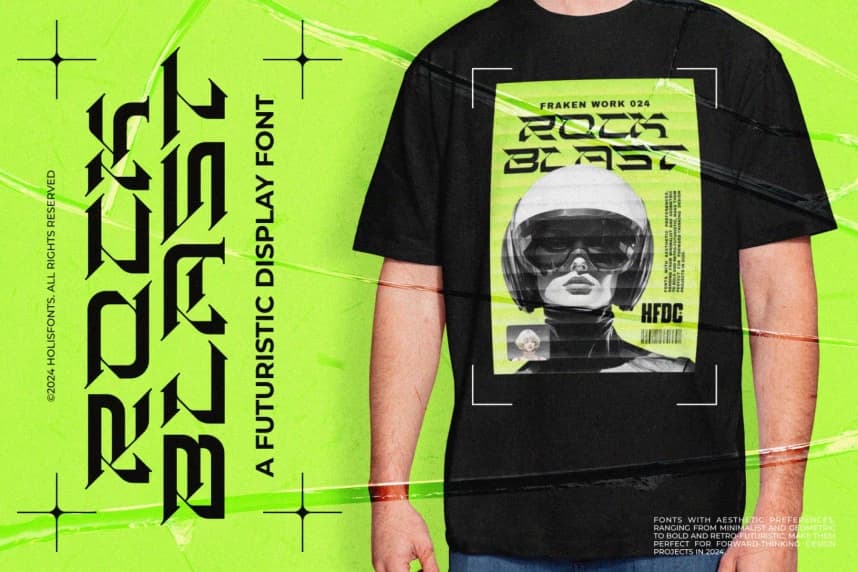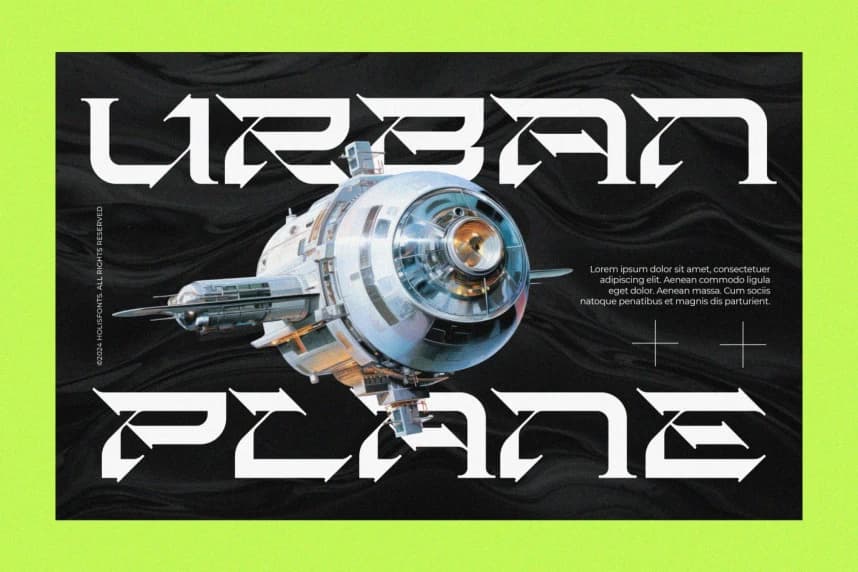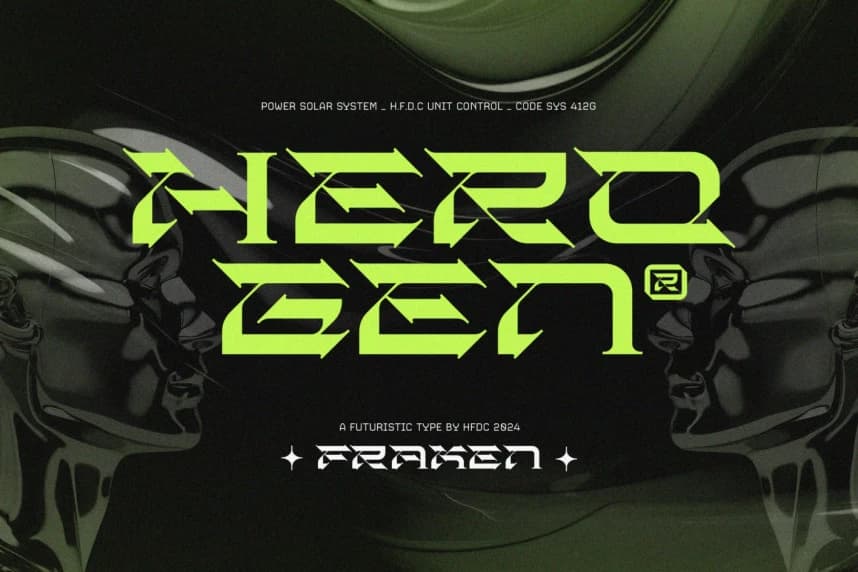
Fraken Futuristic Font
Fraken Futuristic Font, alternatif özelliklere sahip büyük harflerle geometrik estetik harf şekilleri sunar. Geniş ve etkileyici tasarımına sahip olan ve her harfte kalın ile ince hatların bir kombinasyonunu içeren bu yazı tipi, yüksek teknolojik çekiciliğini vurgulayacaktır.
Fraken Futuristic Font, alternatif özelliklere sahip büyük harflerle geometrik estetik harf şekilleri sunar. Geniş ve etkileyici tasarımıyla ve her harfte kalın ile ince hatların bir kombinasyonu sayesinde yüksek teknolojili çekiciliğini vurgular.